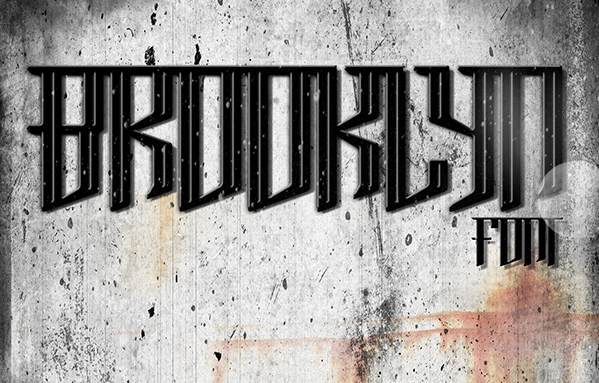
Brooklyn Font – Download Grátis
A Brooklyn Font é uma tipografia baseada na caligrafia que traz uma mistura única de elegância e brutalidade. Esta é uma fonte gothic livre para download, perfeita para quem procura um tom inovador para o design de gráficos. Inspirado na arquitetura do Brooklyn, nos edifícios altos, nas calçadas movimentadas ou no skyline noturno da cidade, essa tipografia se destaca por seu equilíbrio entre linhas curvas leves e robustez angular. Seja para projetos de design gráfico, publicidade ou arte digital, a Brooklyn Font oferece um aspecto único que certamente irá destacar qualquer projeto. Ideal tanto para criar uma identidade visual única quanto para dar um toque distintivo às suas criações visuais.